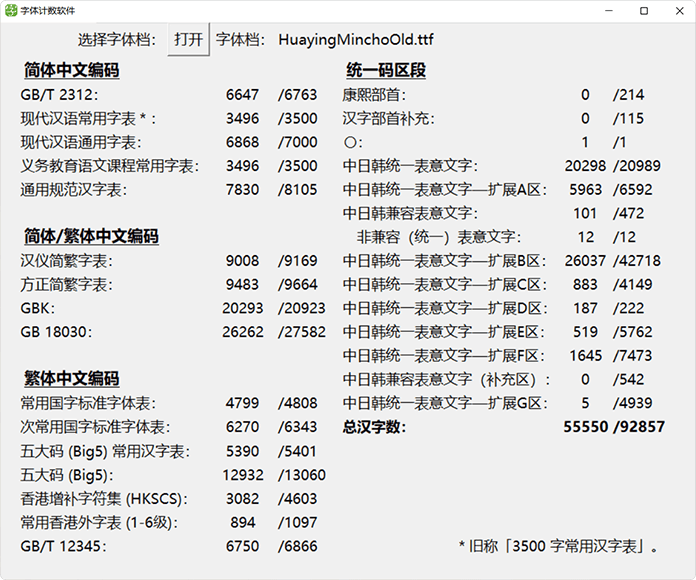
华英明朝:一套拥有传承字形、旧字形风格的中文字体
Huaying Mincho 华英明朝是一套拥有传承字形、旧字形风格的中文字体。华英明朝共提供 3 种字形风格,并带有符合 IVD_Charts_Moji_Joho 标准的异体选择器。
版本说明
1. 华英明朝 旧印体
旧印刷体,字形接近新细明体(旧版)。
2. 华英明朝 传承体
传承字形,字形部件较为统一。
3. 华英明朝 旧典体
接近《康熙字典》中的字形,字形部件不统一。
4. 华英明朝 繁体
由传承体修改,可实现简入繁出的字体。